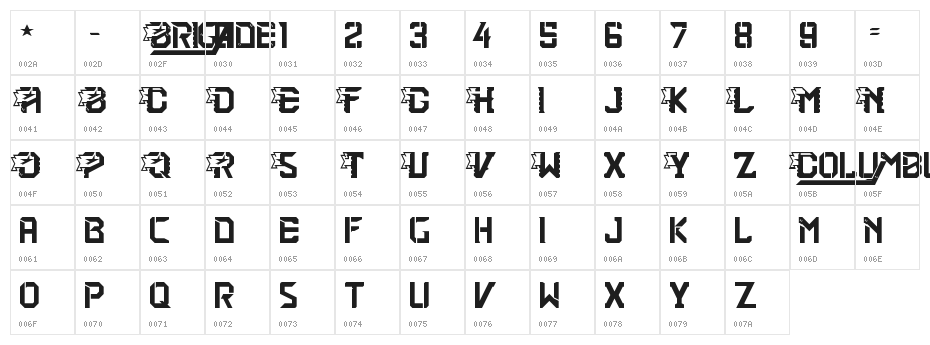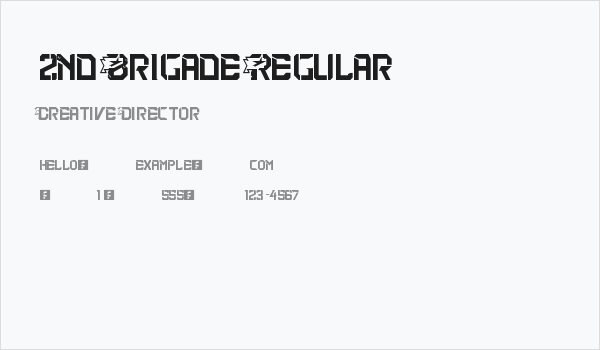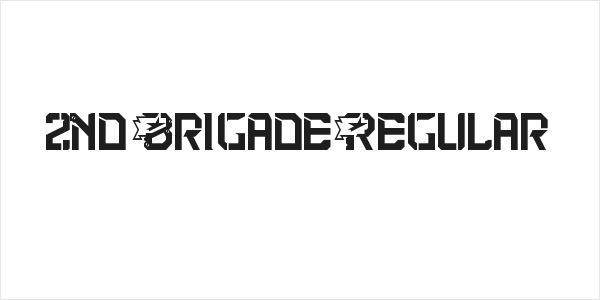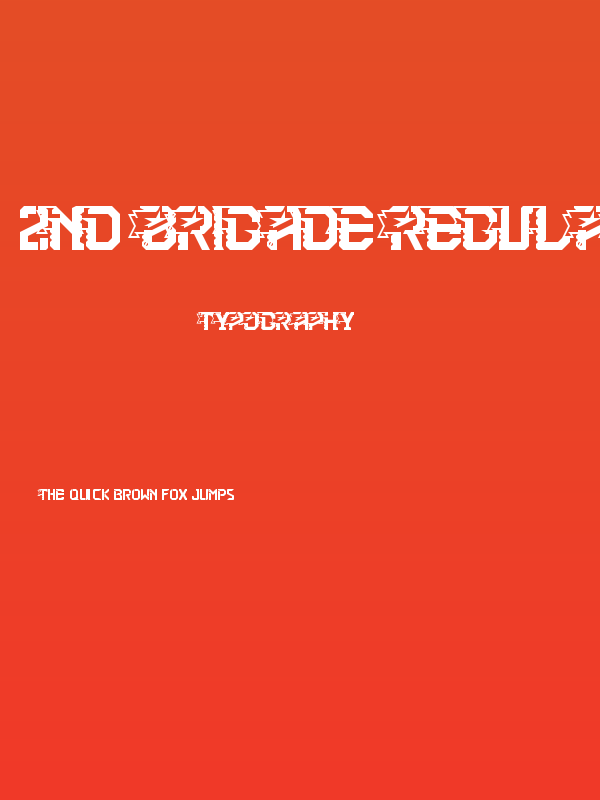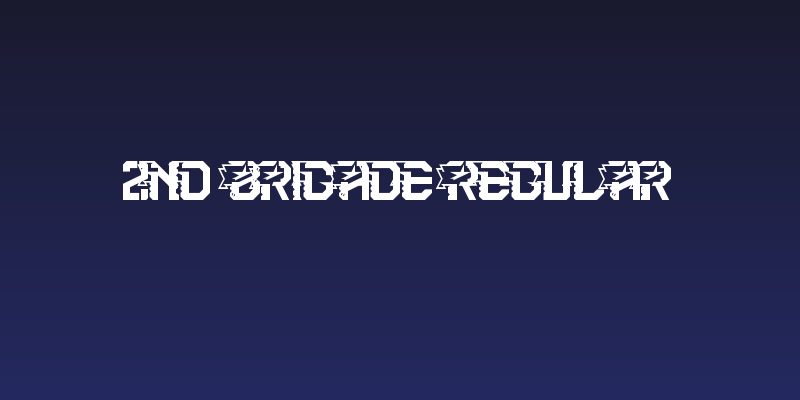
2nd Brigade Regular Font
✎ Stencil
Bill Walker
| 分类 | Stencil |
| 推荐项目 | Ideal for military-themed posters, video game titles, branding for tactical gear, and sports team logos. |